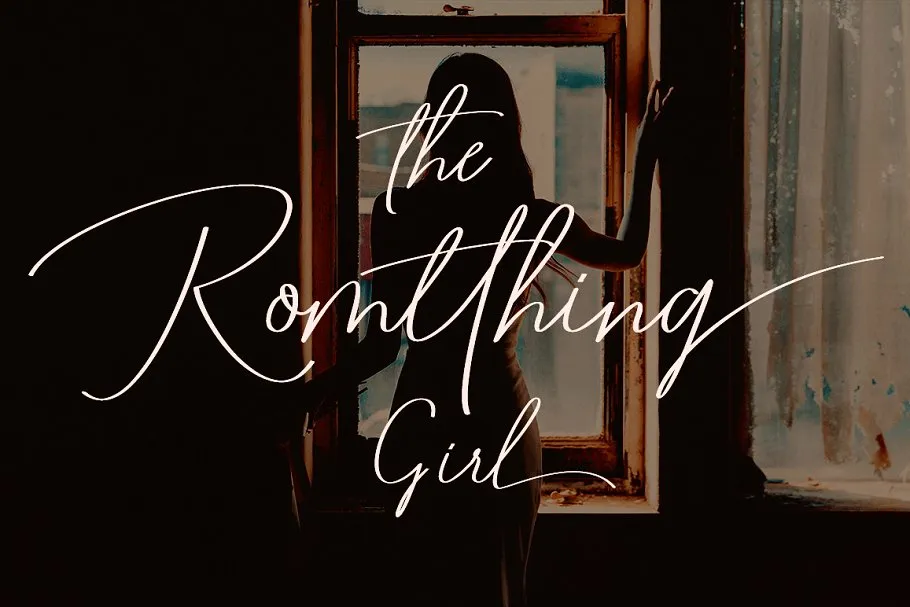
Romtthing Girl Signature Font
Esta é uma fonte de escrita a mão clássica com um toque moderno. Adicione-a à sua coleção de fonts agora. Introduzimos Romtthing Girl Font! Esta foi criada e compartilhada por DoeL. Romtthing Girl é uma fonte simples e elegante, vem equipada com variações elegantes, recursos OpenType que incluem alternativas estilizadas, formatação inicial e final. A Romtthing Girl tem 500 guiacos e ligaturas. A Romtthing Girl é a escolha perfeita para fotografia, assinatura ou design de logotipo de assinatura, citações, capas de álbuns, cartões de visita e muitos outros projetos de design. Desde cartões de visita até marcas d’água em fotos, porque a Romtthing Girl é uma assinatura elegante com luxo.